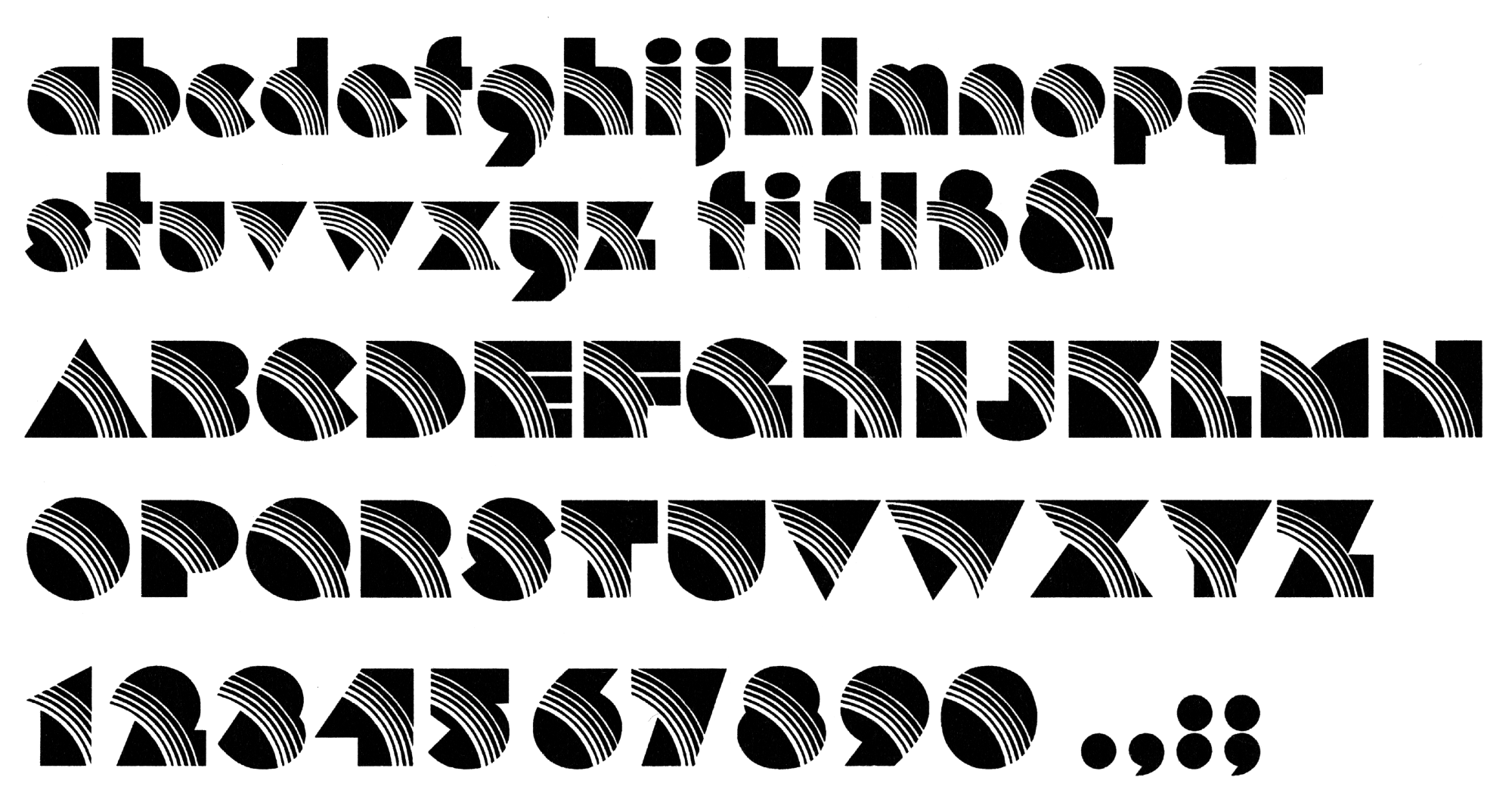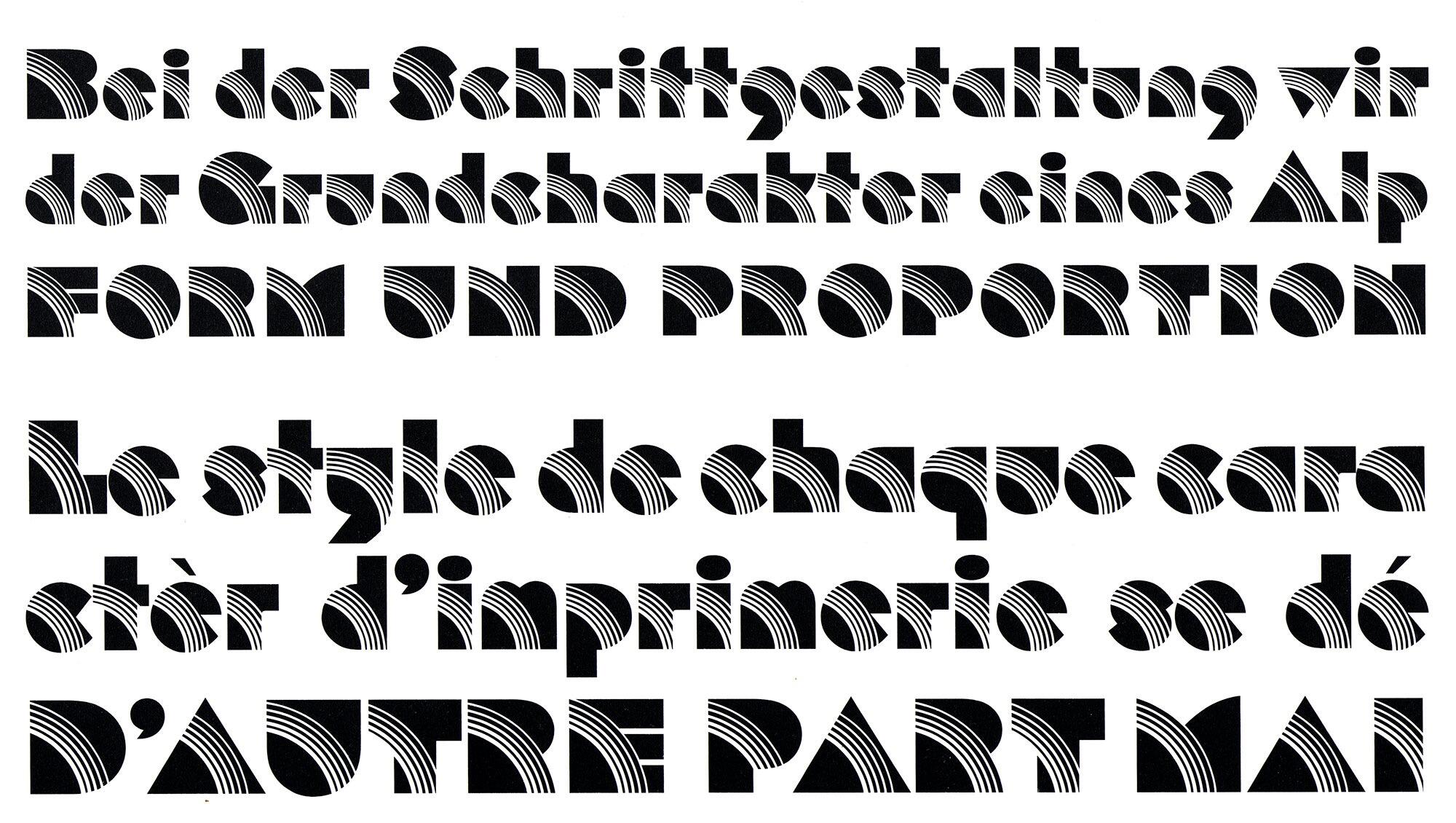
Die Rainbow Bass, benannt nach ihrem Schriftgestalter Saul Bass, erschien in den 1980er-Jahren als Fotosatzschrift über Mergenthaler-Linotype.
Eine Digitalisierung ist über Nick’s Fonts als Kymmera Deco NF erhältlich.